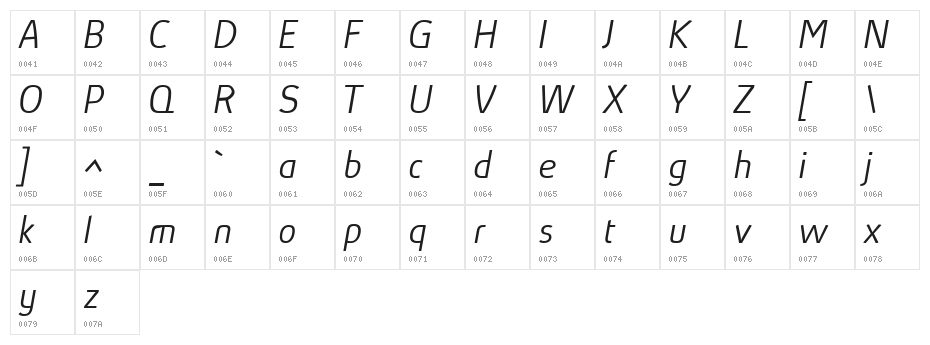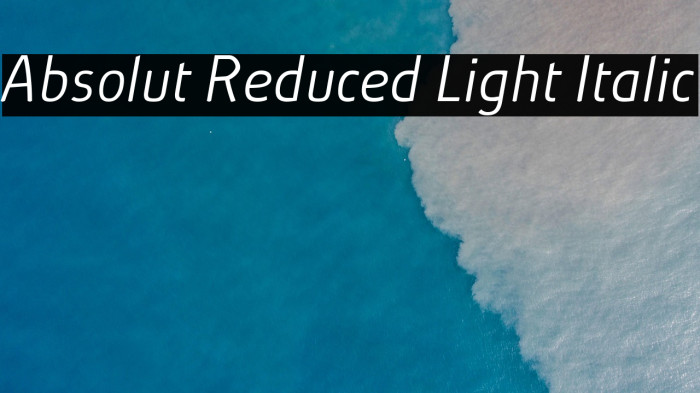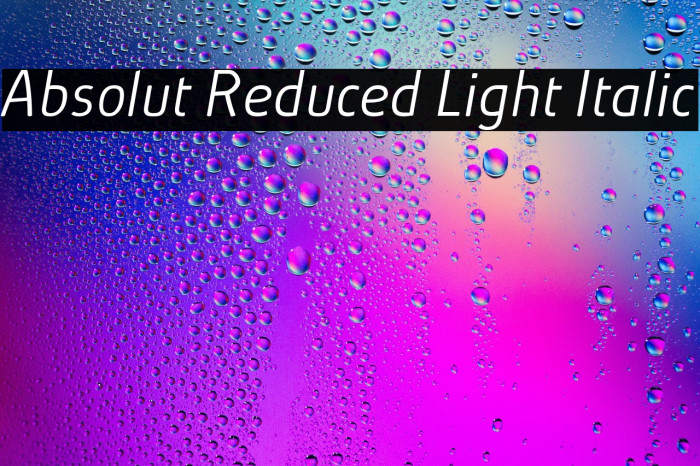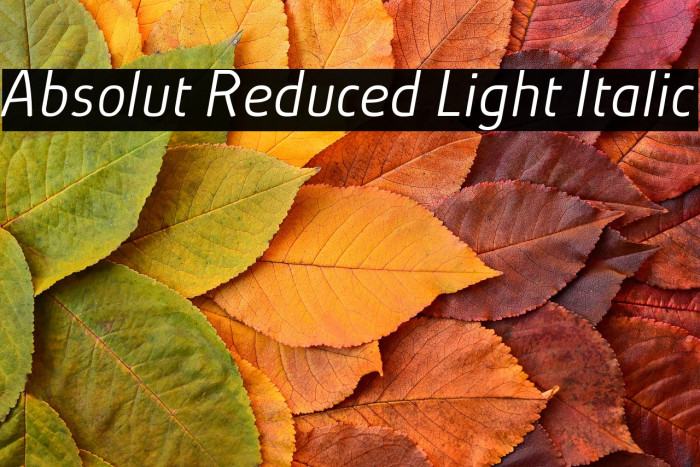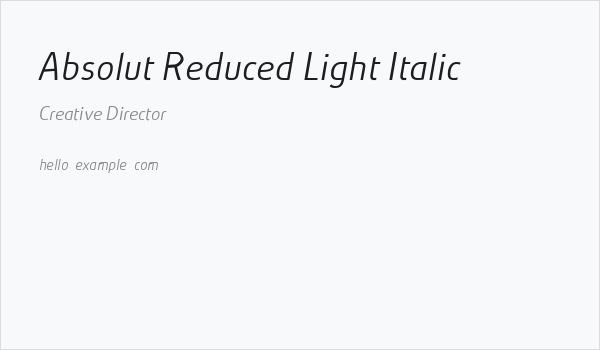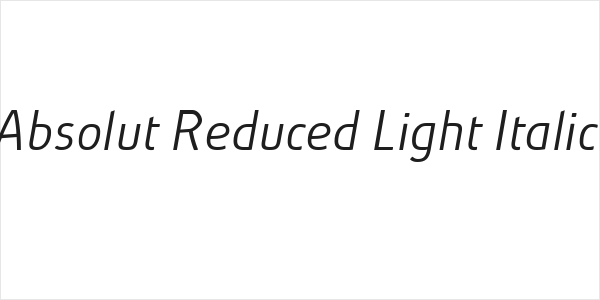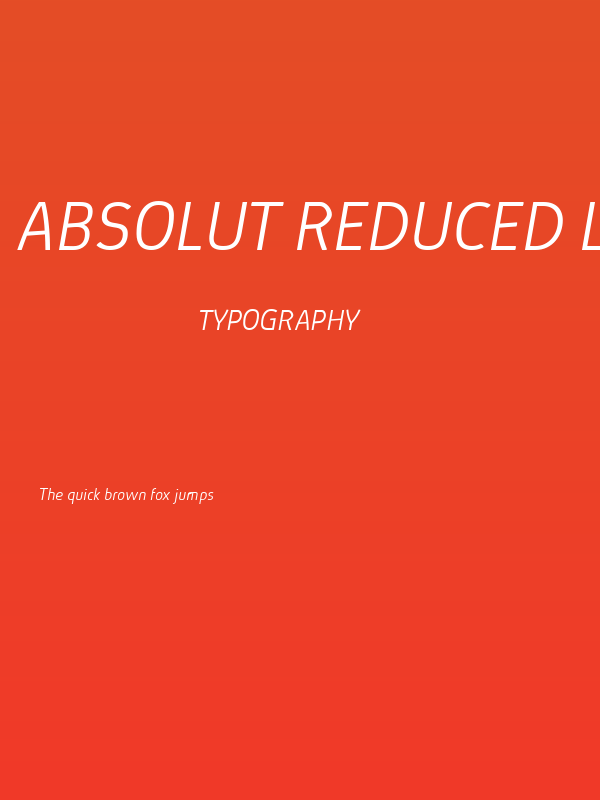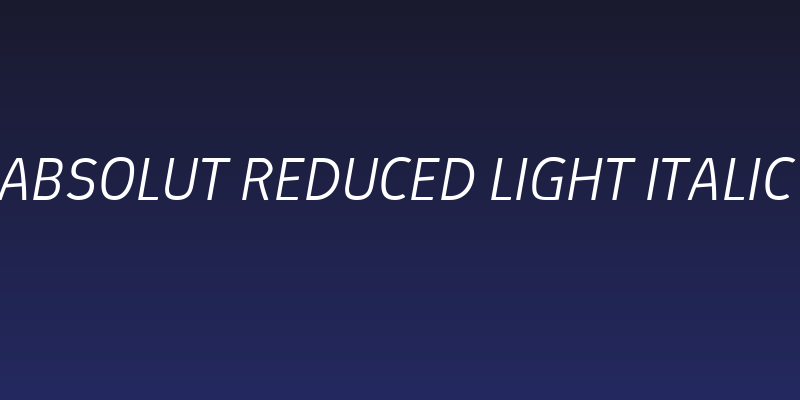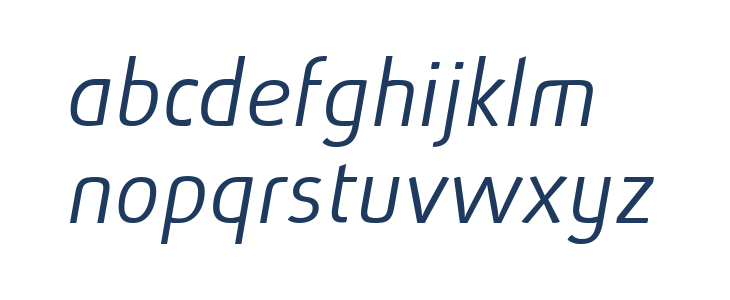
Absolut Reduced Light Italic Font
| Progetti proposti | Ideal for branding, editorial design, and digital interfaces where a modern and clean aesthetic is desired. |